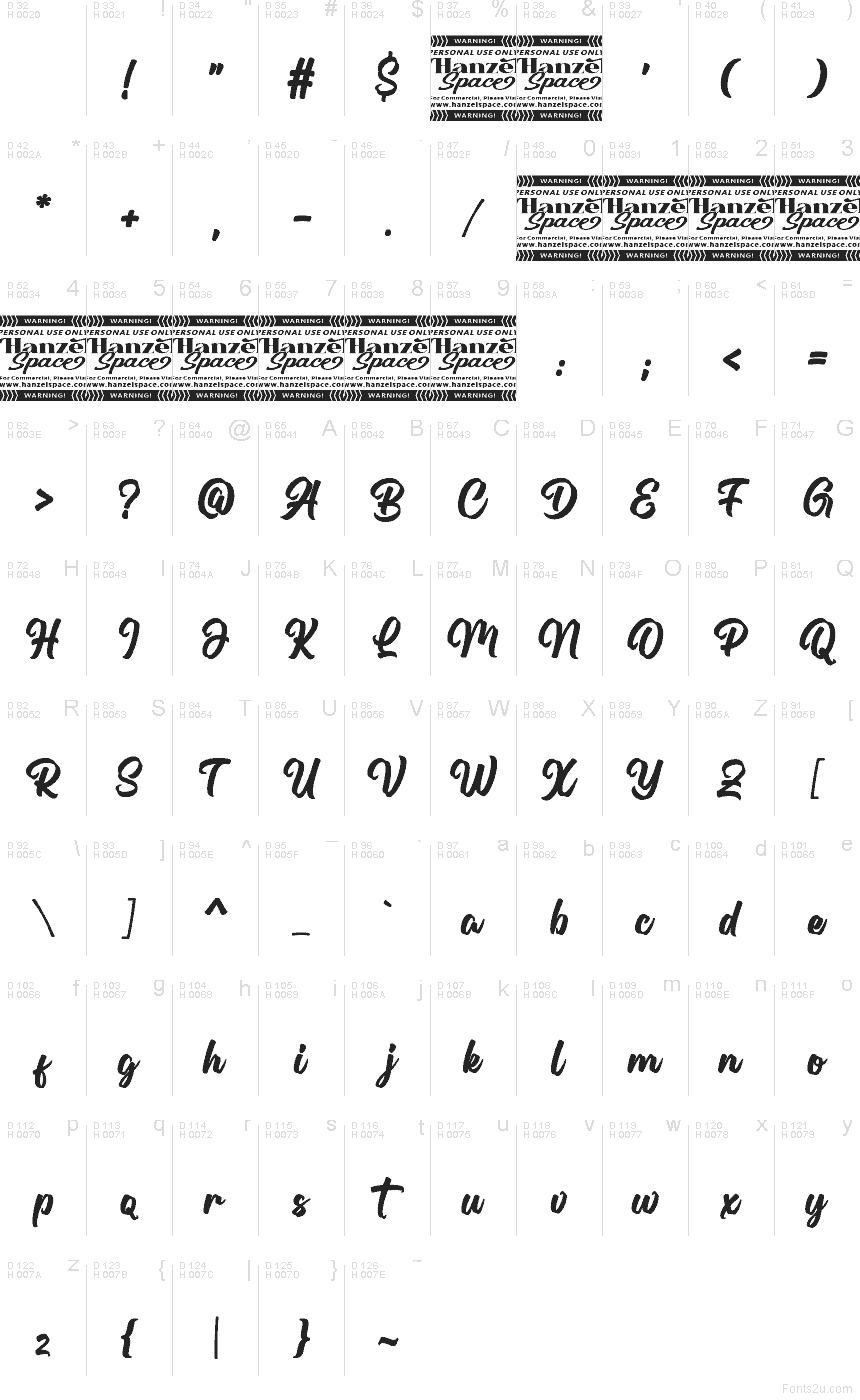
British Letter to darmowy krój pisma typu brush calligraphy o luźnym, nowoczesnym charakterze. Litery balansują między szerokimi, pełnymi pociągnięciami a szybkimi, zwężanymi łączeniami, co nadaje mu wygląd ręcznie malowanego napisu. Zaokrąglone pętle i lekko nieregularny rytm sprawiają, że pismo wygląda naturalnie i „ludzko”, a nie sztywno i formalnie.
Idealnie sprawdzi się w brandingu kawiarni i butików, na plakatach, opakowaniach, okładkach albumów czy grafikach do mediów społecznościowych – wszędzie tam, gdzie potrzebujesz ruchu, a nie wygładzonej perfekcji. Użyj go, gdy chcesz, by krótkie hasła, imiona czy nagłówki wyglądały jak napisane jednym, pewnym ruchem ręki – połączone formy i wyrazista tekstura pędzla zrobią wrażenie za Ciebie.